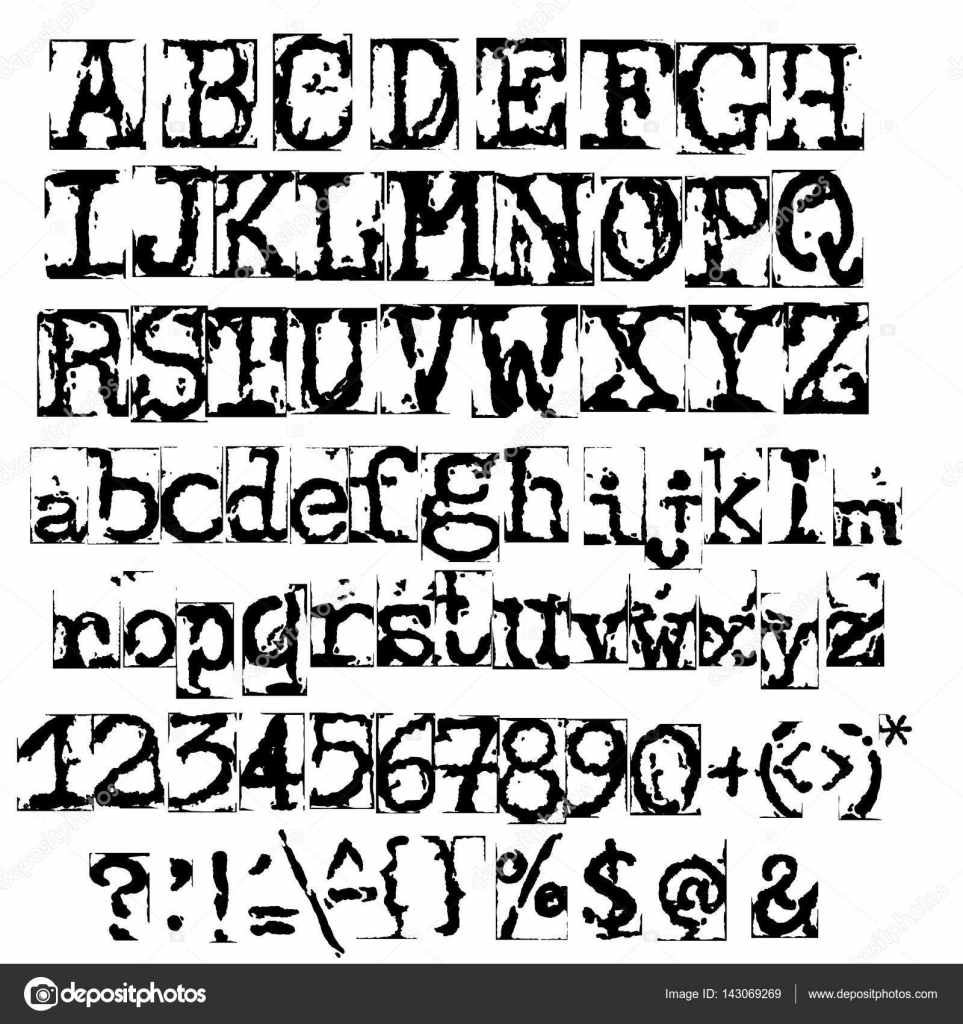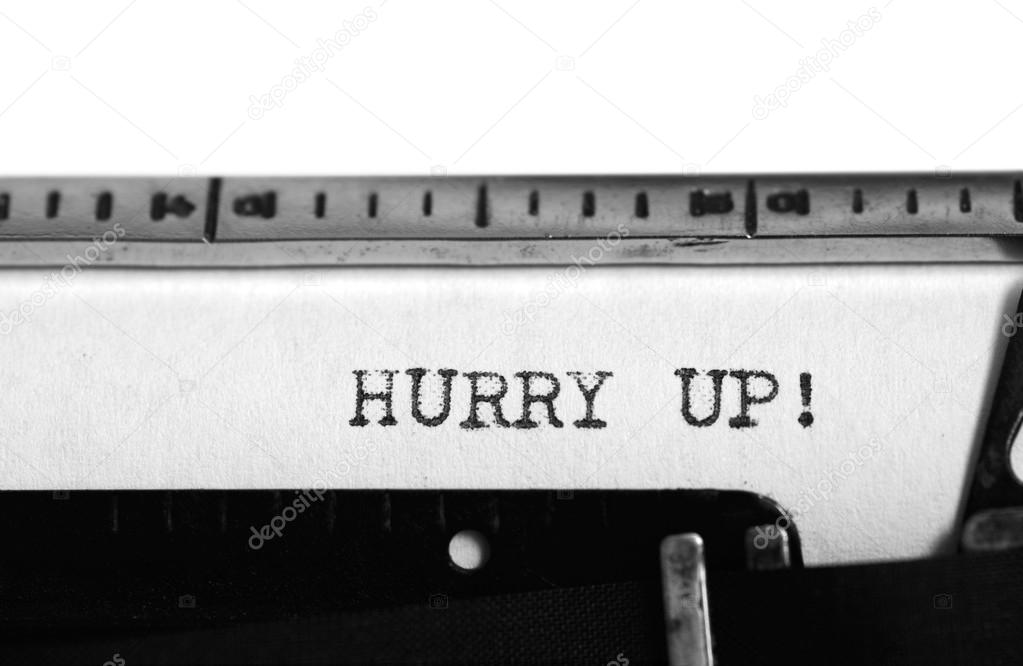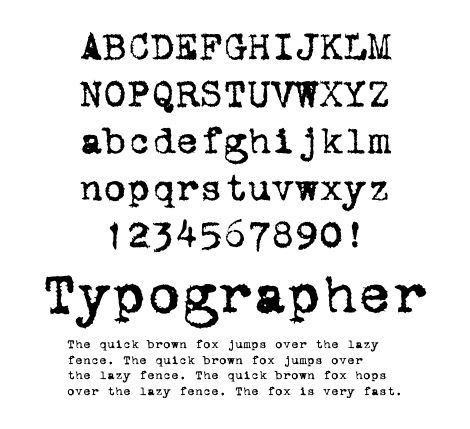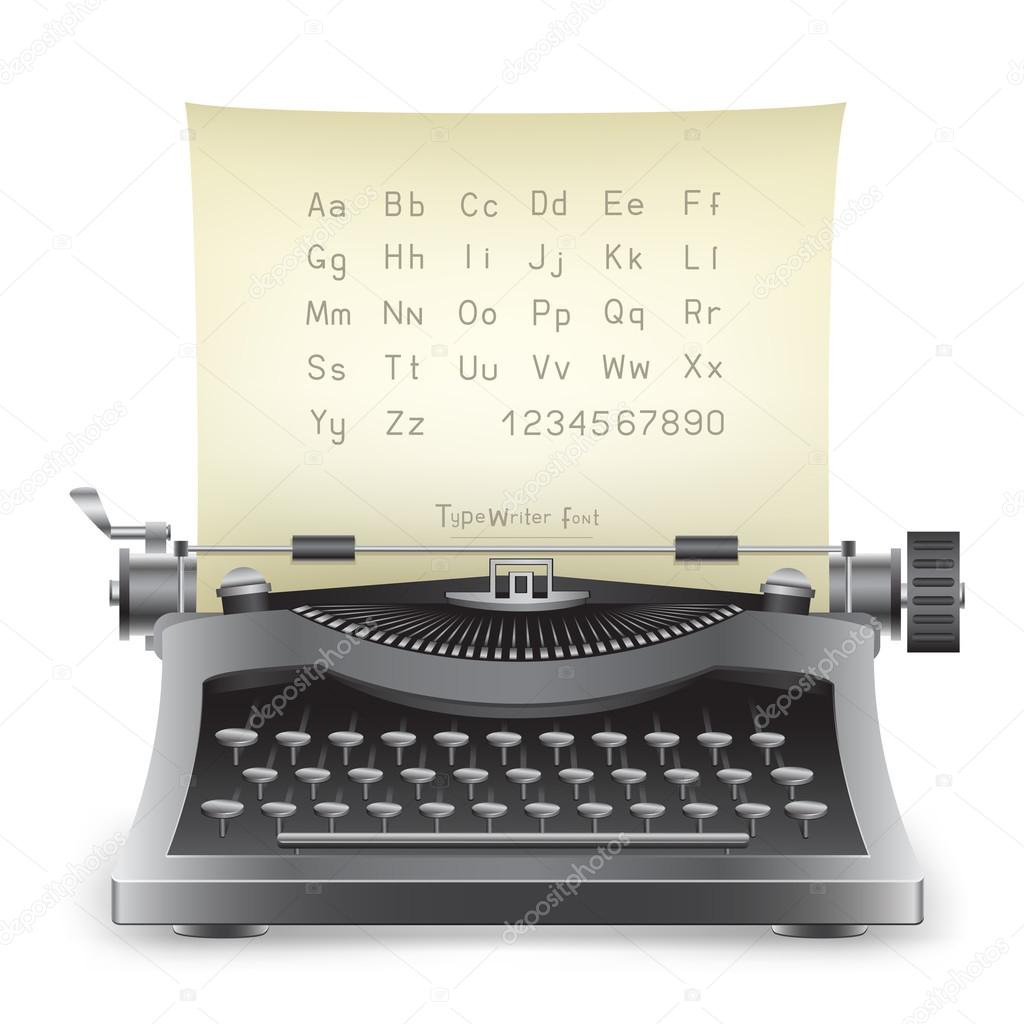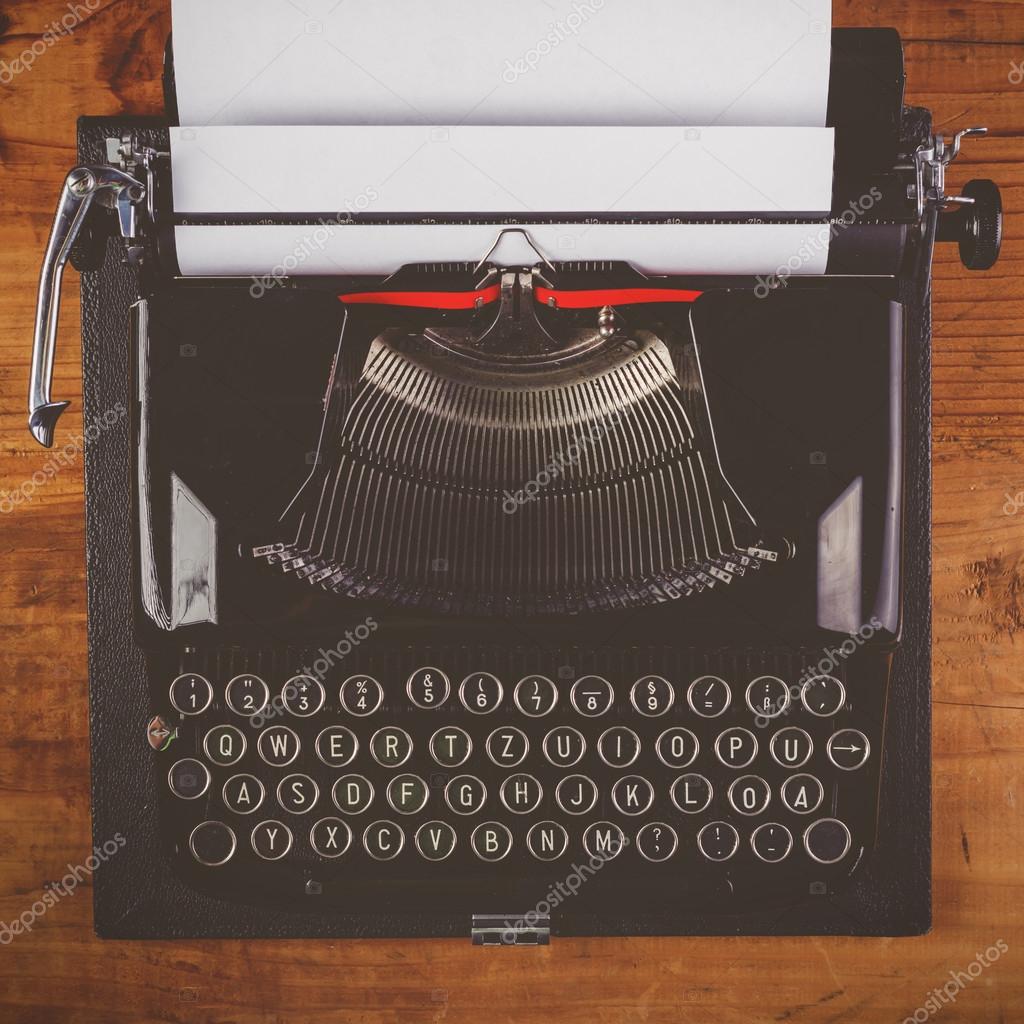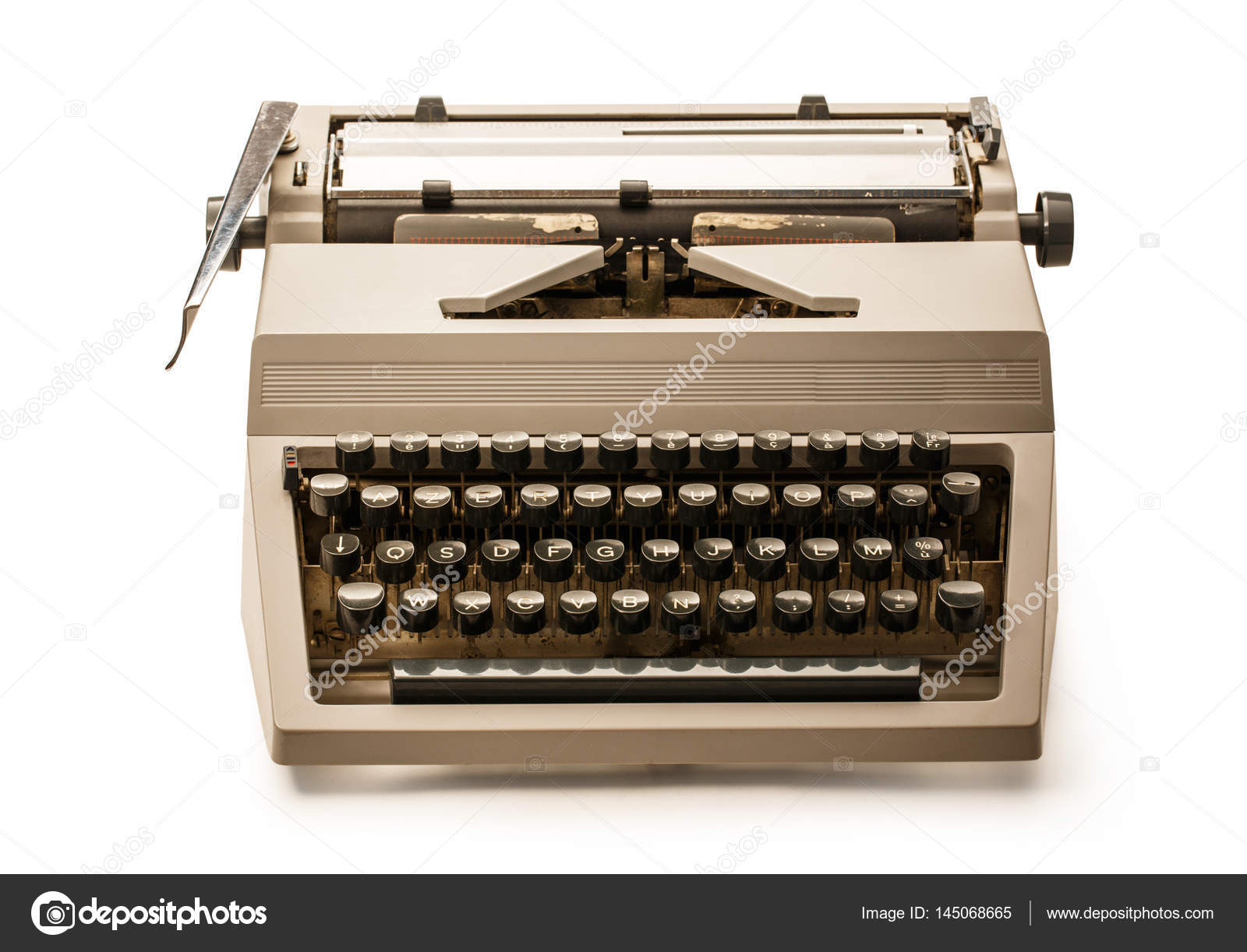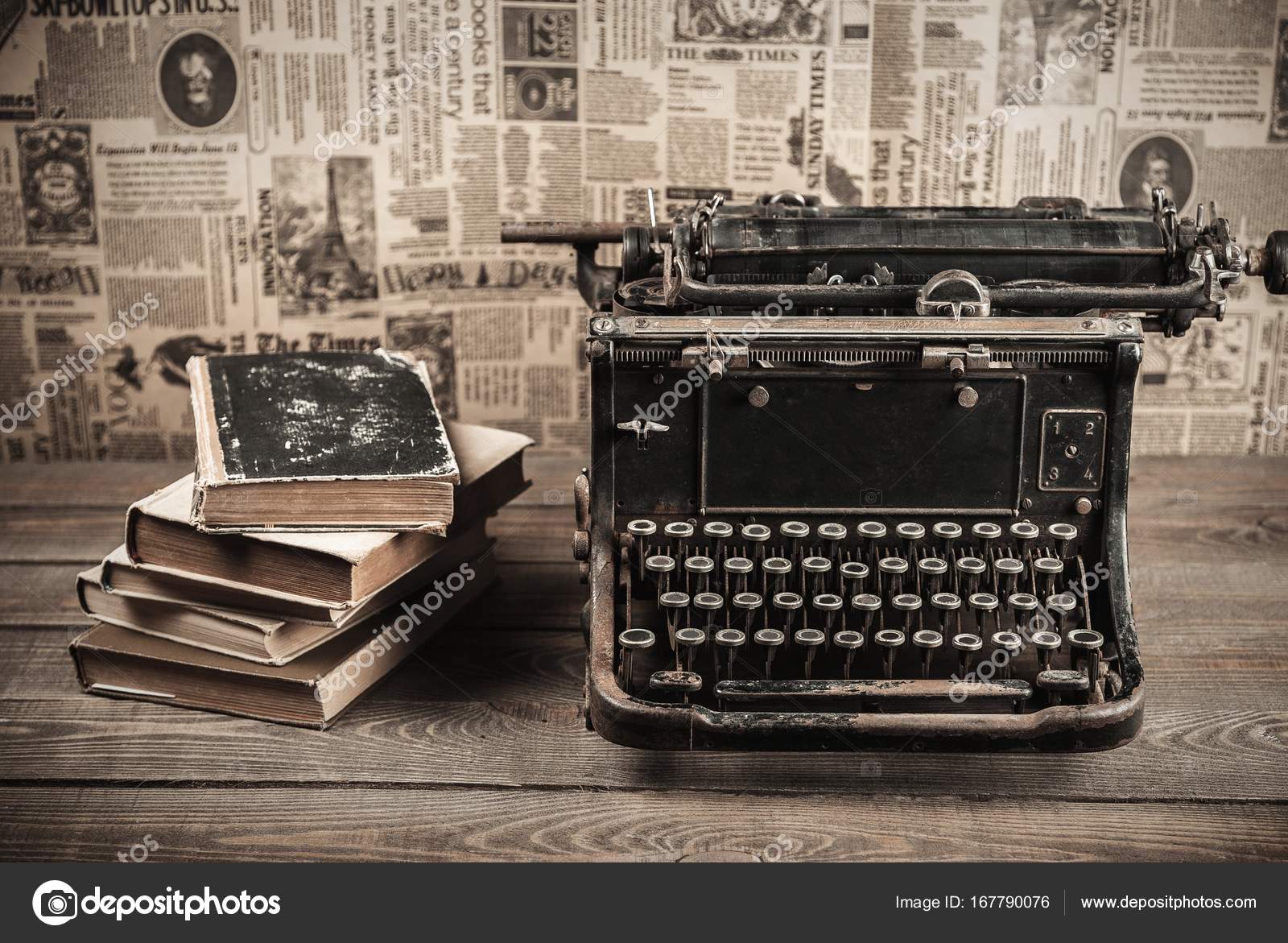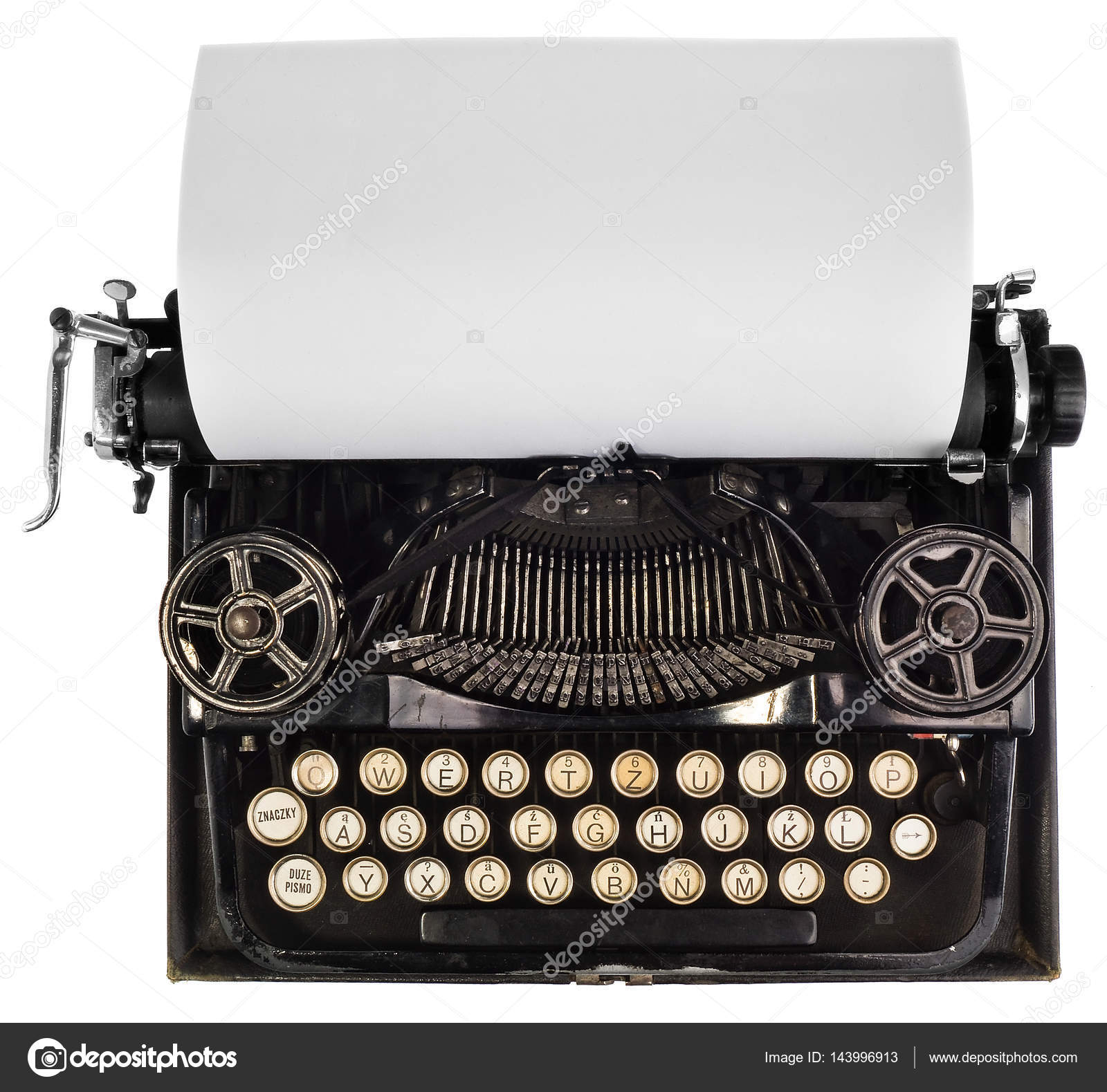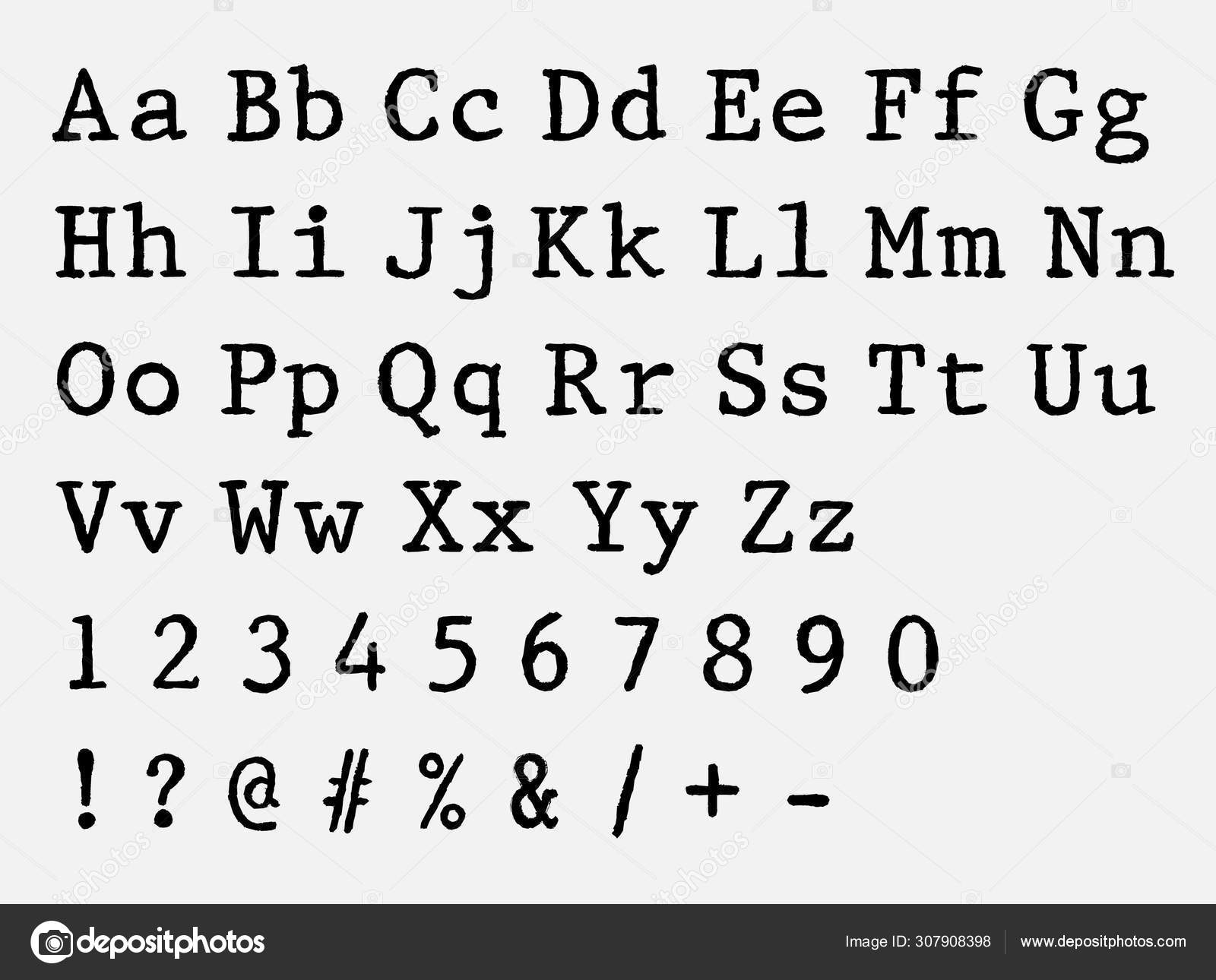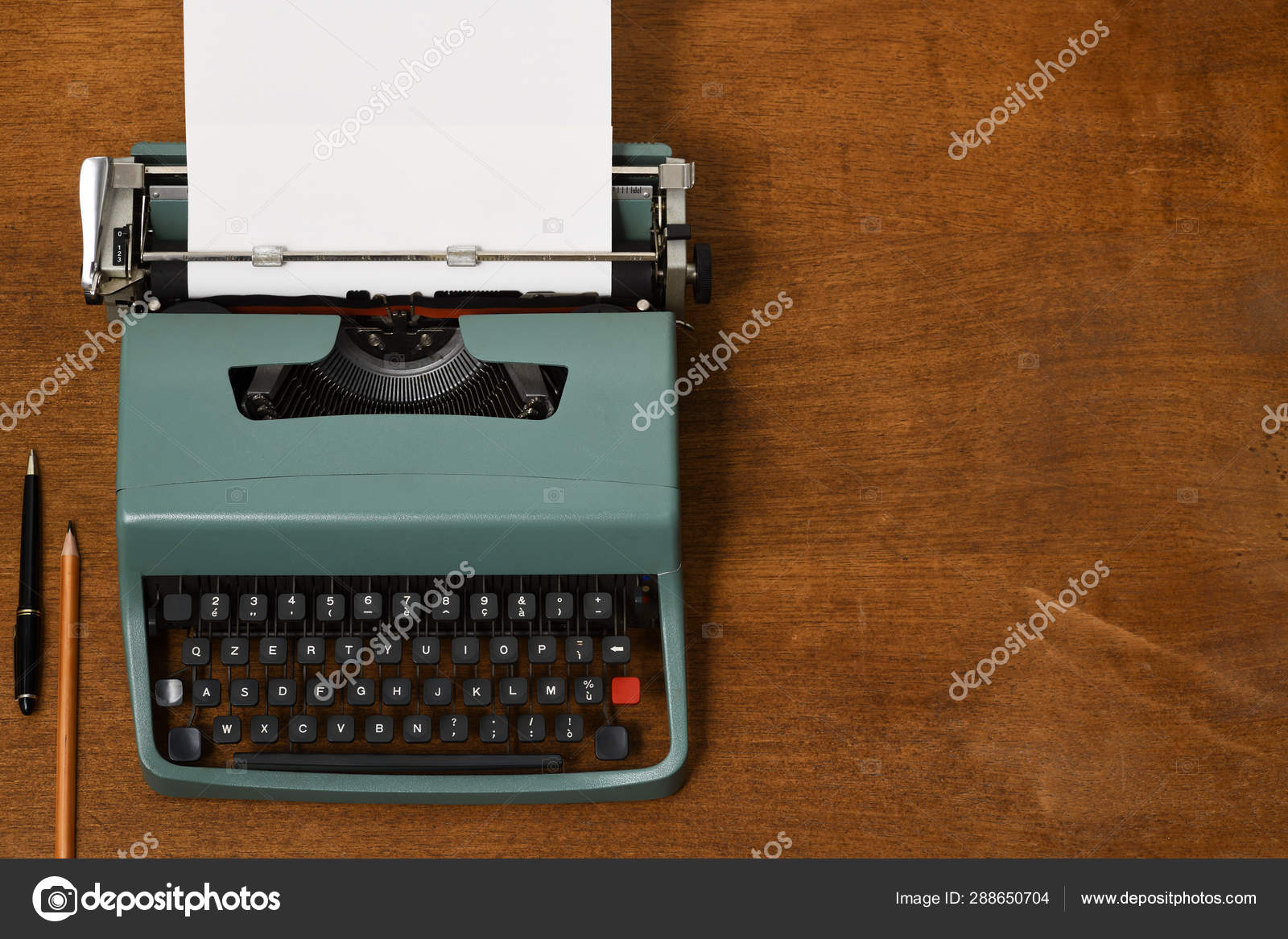
Лучшие печатные шрифты для Word и Фотошопа (+русские)
Название сегодняшних материалов в подборке полностью определяется способом их создания — это шрифты печатной машинкой. Теоретически, по форме и стилистике они должны соответствовать реально напечатанным текстам. Похожий принцип типографики встречался в заметках про граффити или надписи мелом на доске — по данным наименованиям вы сразу четко представляете их внешний вид.
Если говорить о визуальной составляющей, то тут все достаточно тривиально. В целом нет такого разнообразия как в декоративных и оригинальных шрифтах. Варианты отличаются разве что качеством / силой «оттиска» для букв и наличием неких посторонних «вкраплений»: где-то текст получается более четкий, в других случаях он выглядит слабо пропечатанным.
Brother Deluxe 1350
1942 Report
Urania Czech Font
My Underwood Font
Tox Typewriter
Through the Night
Typical Writer Font
Kingthings Typewriter
Traveling Typewriter
Rough Typewriter
CarbonType
Harting
Secret Typewriter
Courier Prime
DK Trashtype Font
Love Letter TW
AFL Font Pespaye Nonmetric
Veteran Typewriter
Есть варианты машинописных шрифтов, которые имеют чуть больше декоративных элементов. В принципе, по некоторым заметно, что они не напечатаны, но все же при этом несут в себе схожую интересную стилистику.
NelsonOldNewsPaper Font
Telegraphem
Old printing press
Subway Novella
Punkbabe
Xerography Font
F25 Blackletter Typewriter
Type Keys
Русские печатные шрифты
Дополнительно нашли немного кириллических фонтов для рунета.
TrixieCyr Plain
Bezpredmetizm
DS Moster
B52
a_OldTyperNr Regular
DS VTCorona Cyr
ABC_TypeWriterRussian
Lettera Trentadue
TypeWriter Normal
Prestige-Normal Regular
Vector Old Typewriter Font
Vintage Grunge Typewriter Letters
Alphabet 5 Variations of Every Letter
Typewriter Text on an Aged Paper
Type Writer Alphabet Handmade Letters
Vector Old Typewriter Font
Font Printed on Vintage Typewriter
ABCD Letters Written with a Typewriter